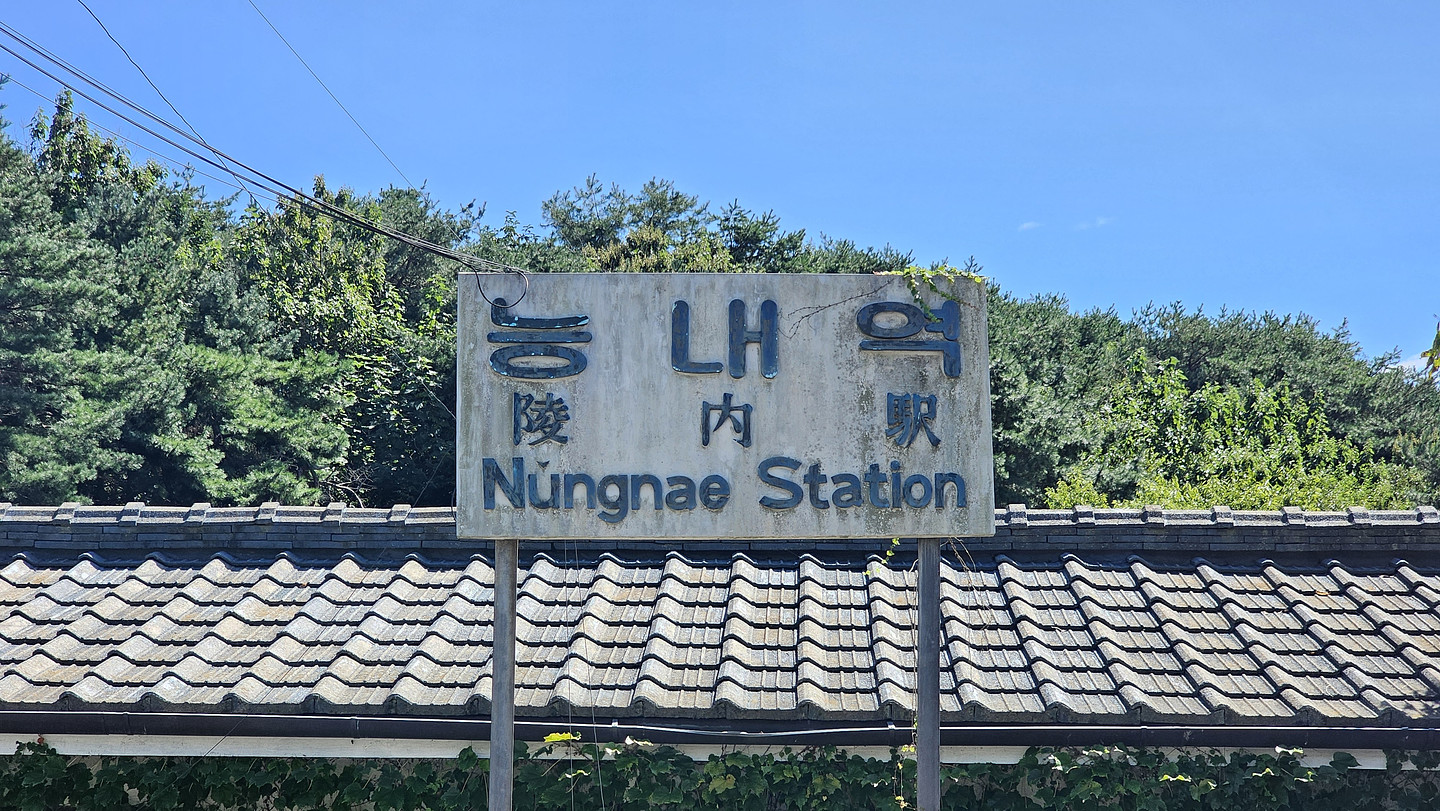
이 사진은 예전 철도역에서 90년대 이전에 써오던(주로 70~80년대) 간이역 역명판의 모습입니다. 이 역명판에 사용된 글씨의 모양은 동시대의 다른 역들도 비슷한데요, 혹시 이러한 역명판에 쓰인 폰트(혹은 이와 비슷한 폰트)를 알고 계시는 분들이 계신가요? 몇 가지 특징으로는, 이 폰트는 대체적으로 모서리가 원형으로 되어 있으며 가로로 매우 긴 것이 특징입니다.